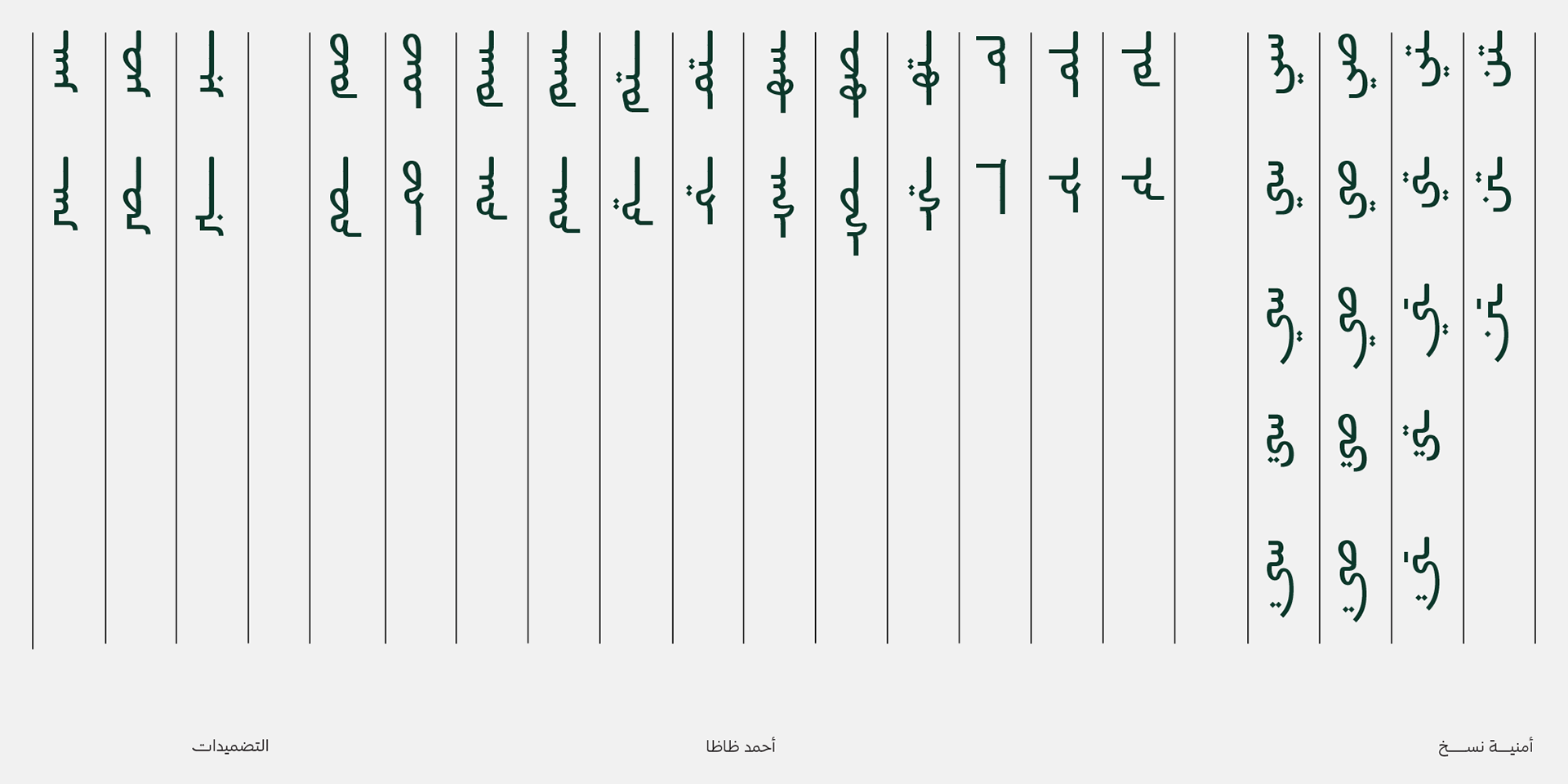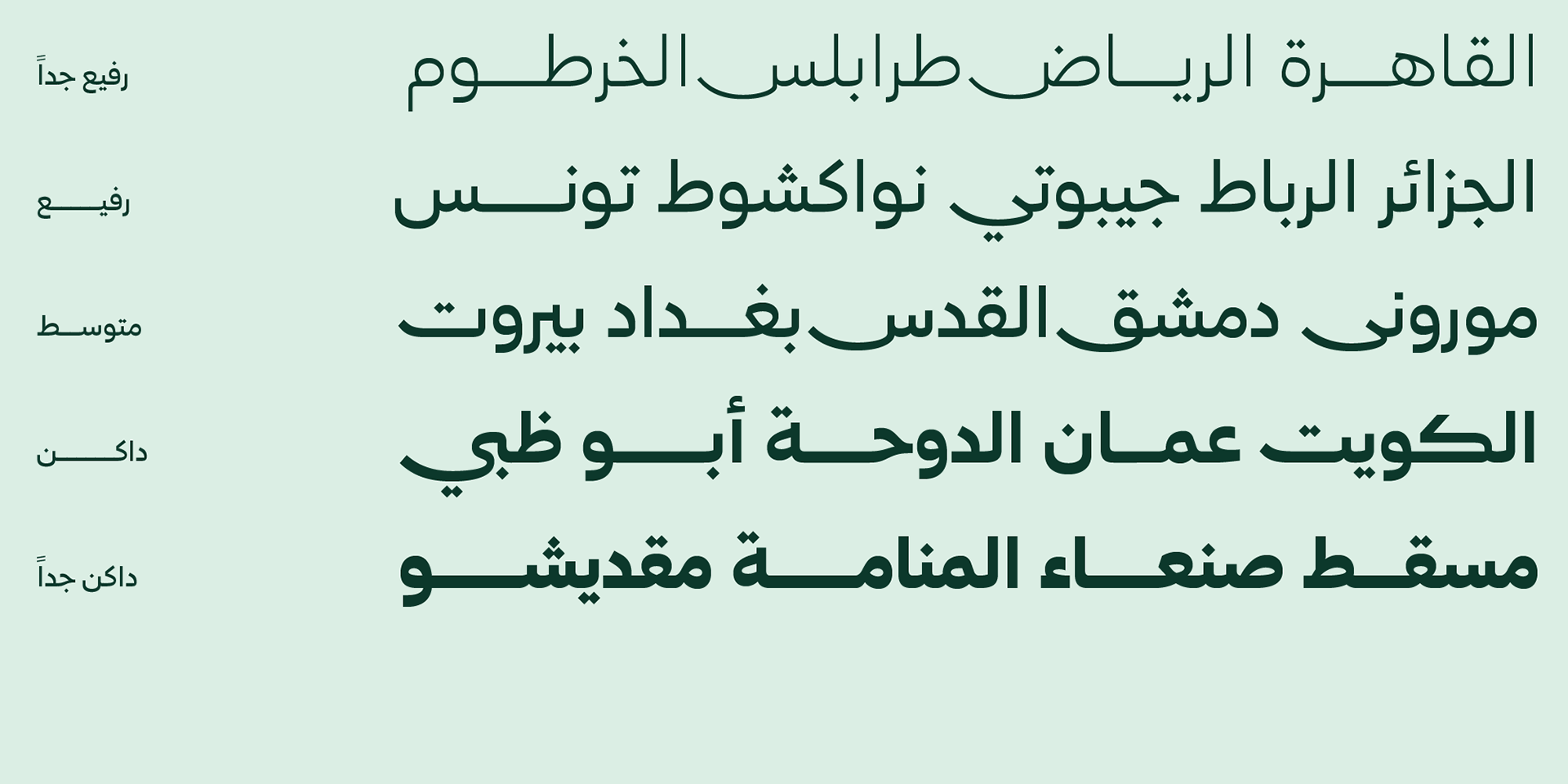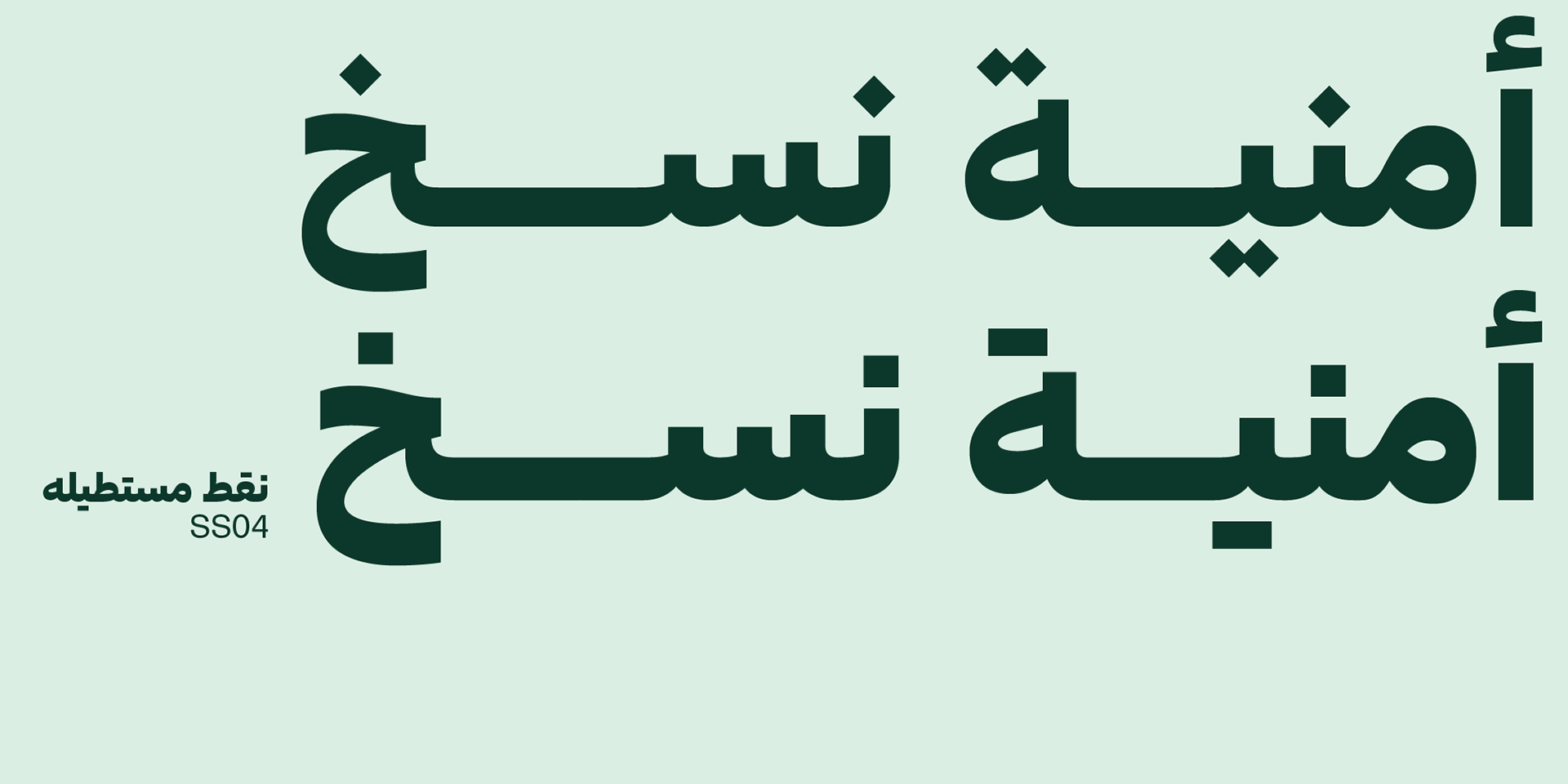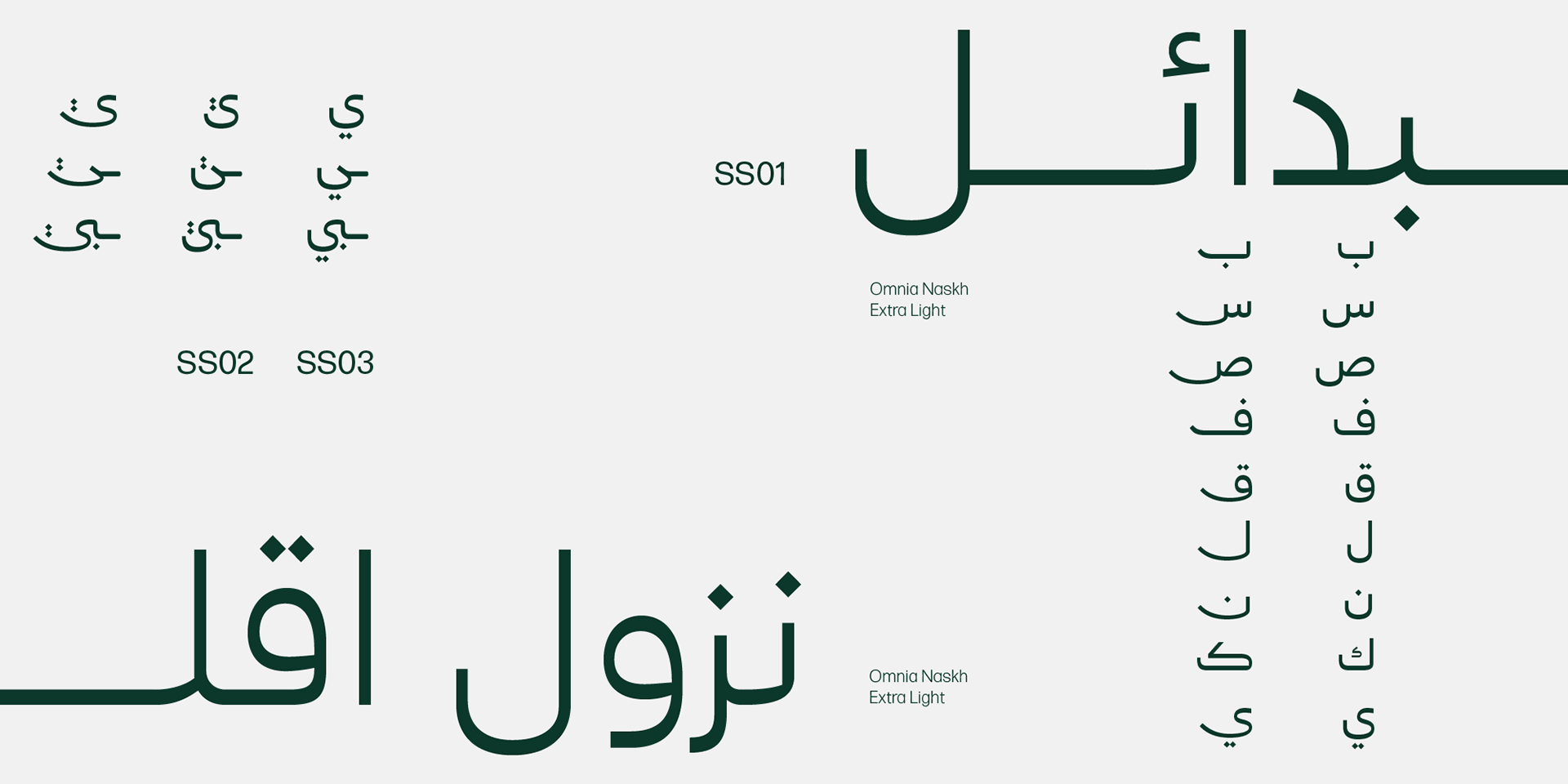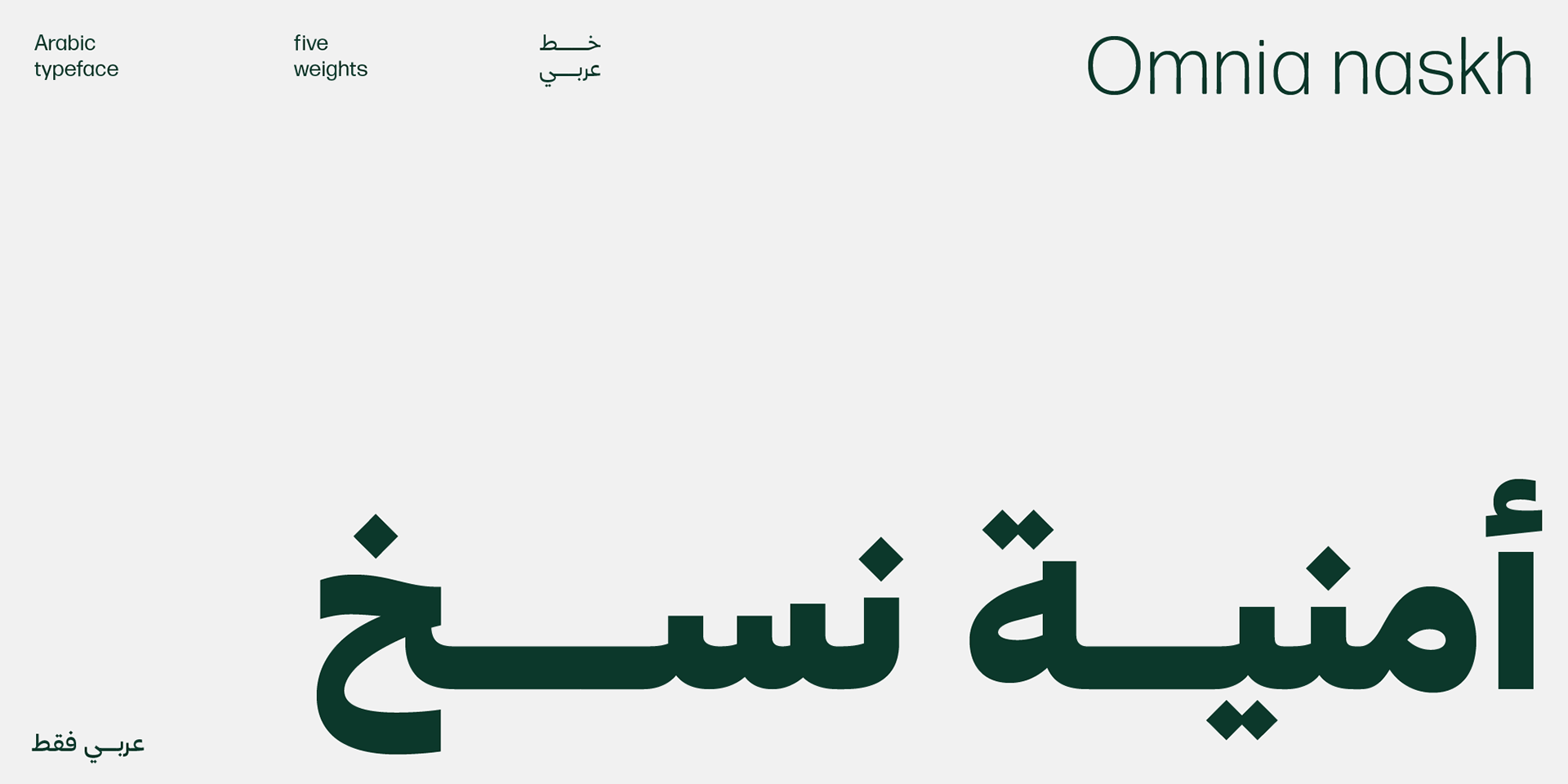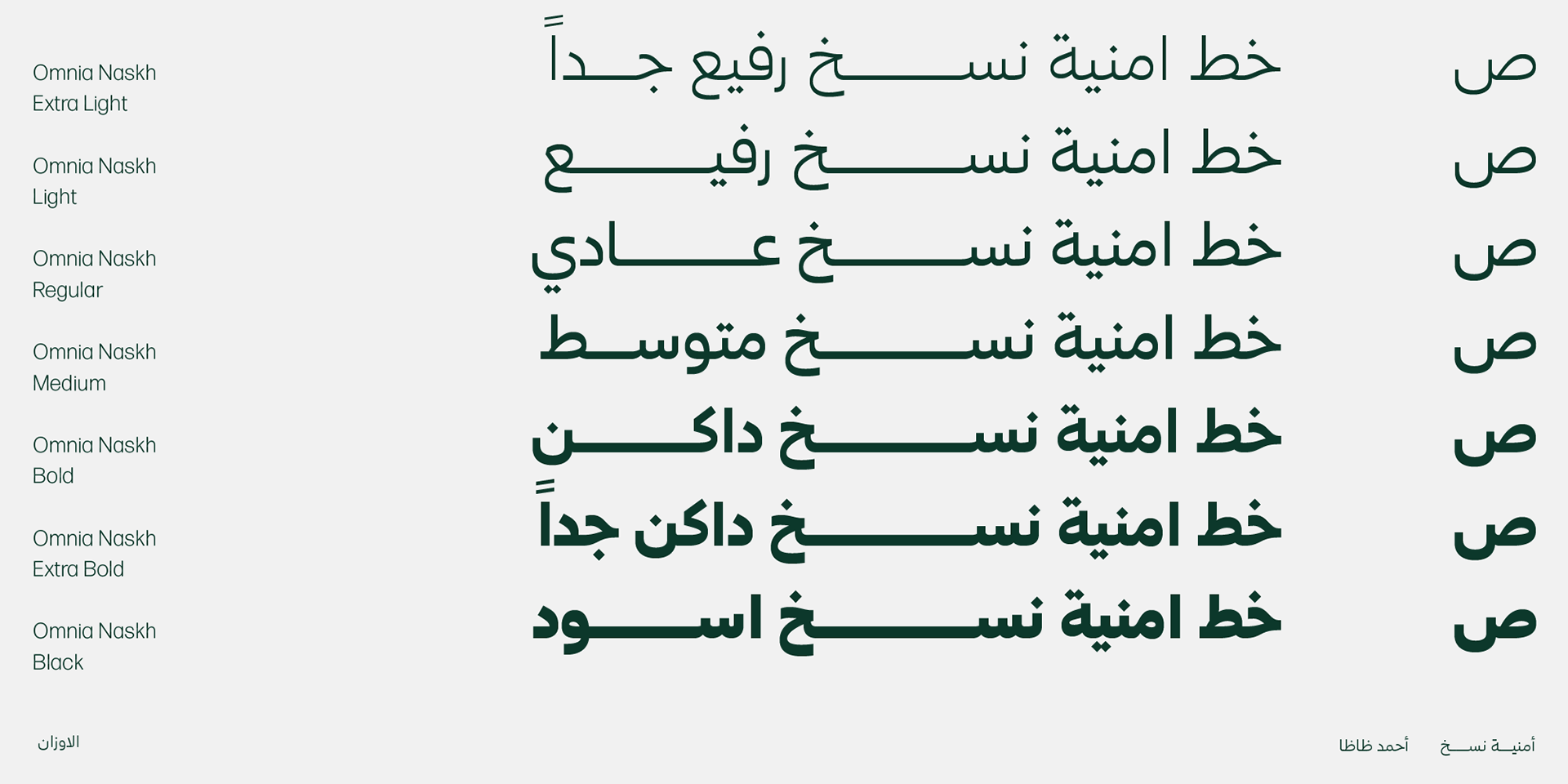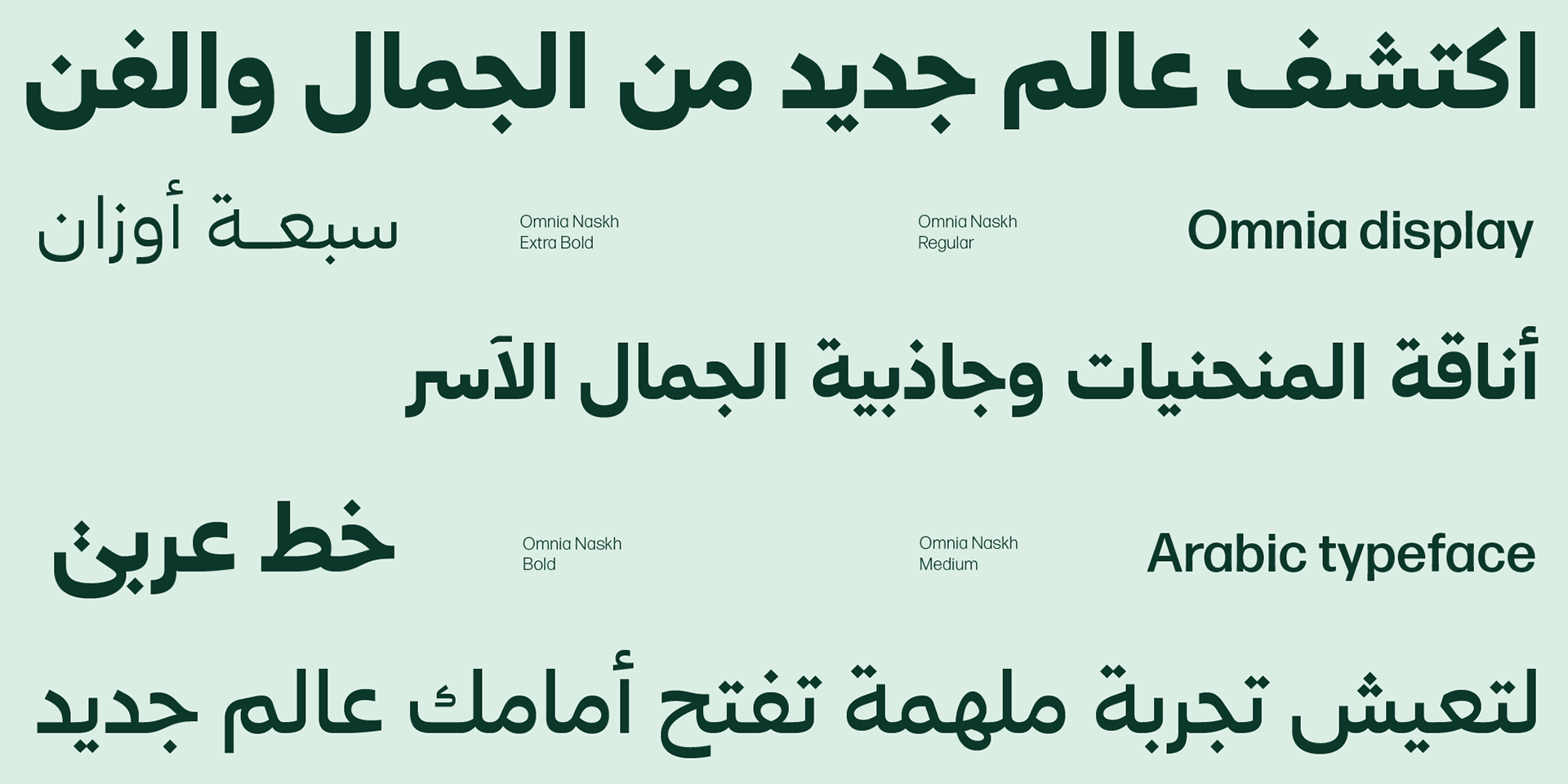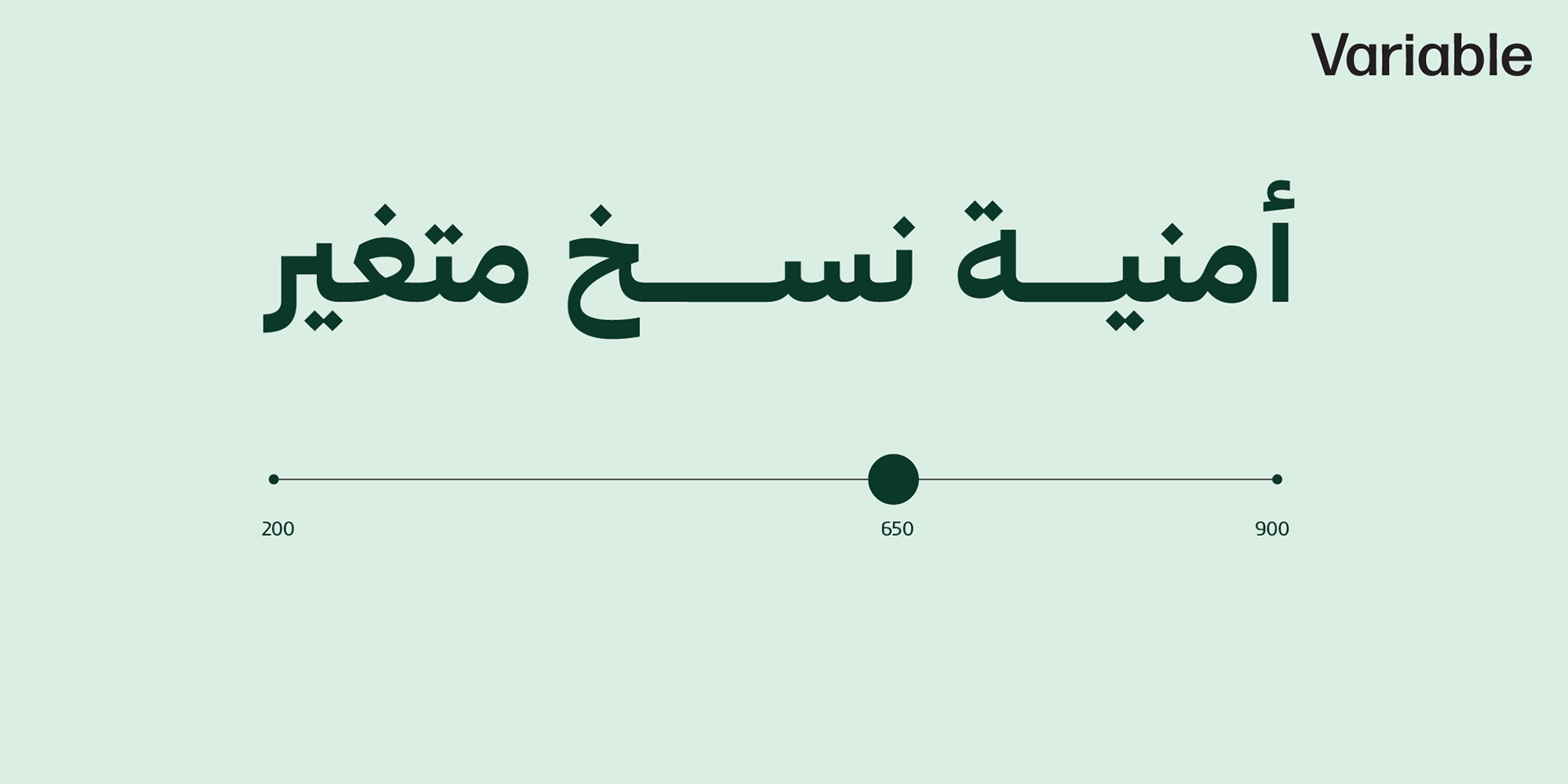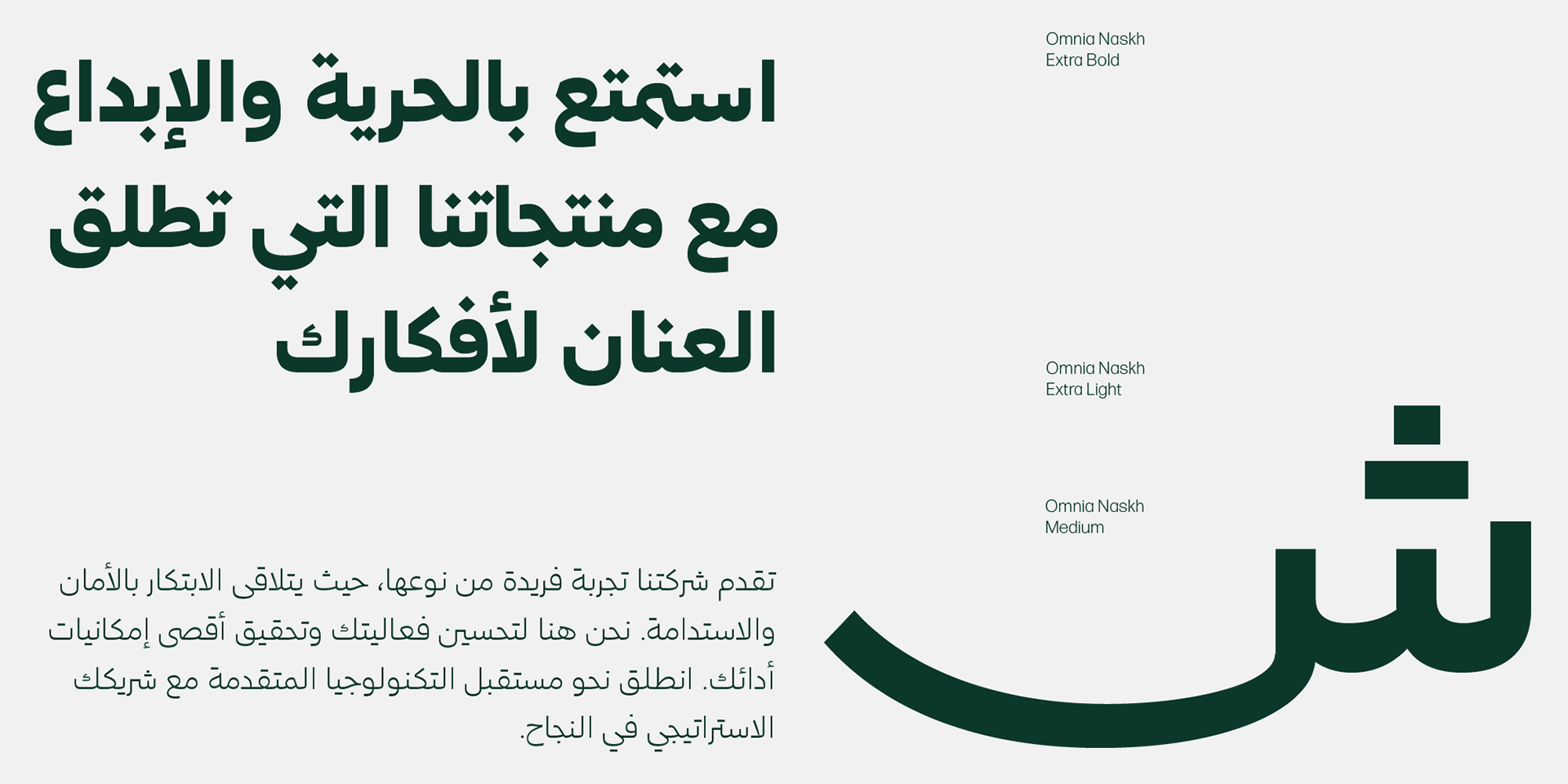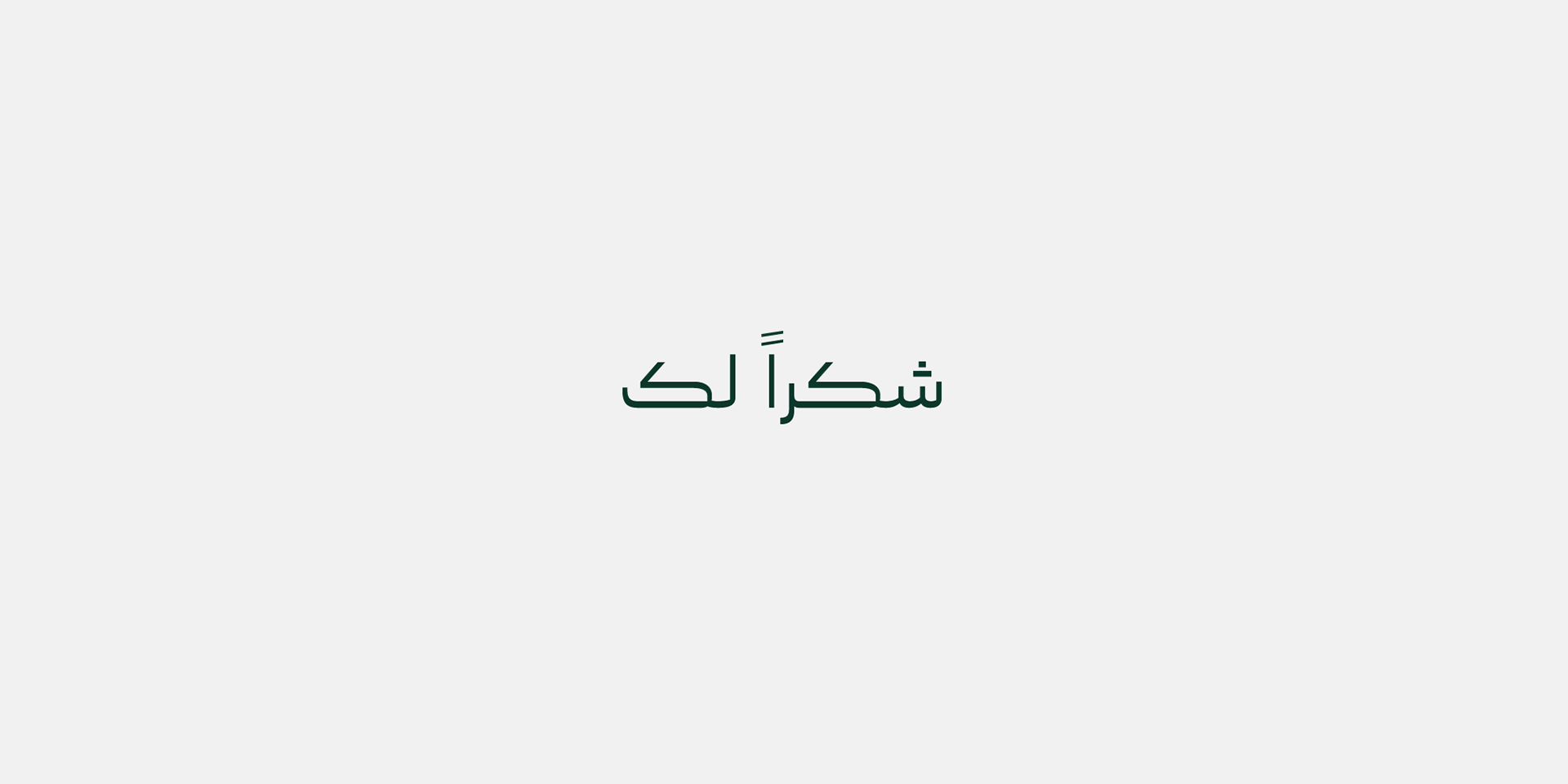
Omnia Naskh typeface - خط أمنية نسخ
أمنية نسخ هو خط عربي نسخ حديث يتميز بالأنحناءات الجمالية التي تعكس دقة التفاصيل. يجمع الخط بين الجمال والدقة في تجربة كتابية فريدة وغنية بالتفاصيل. تبرز مزايا أمنية نسخ بفضل وجود الحروف المركبة والحروف البديلة والحروف المرسلة. تسمح هذه الميزات للمصممين والكتاب بإنشاء نصوص أكثر تنوعًا وجمالًا وتعبيرًا. يتميز أمنية نسخ بوضوح في التصاميم الاحترافية، مما يضمن قراءة سهلة وفهمًا واضحًا. أمنية نسخ هو خيار احترافي يناسب مجموعة واسعة من الاستخدامات، بما في ذلك الطباعة والتصميم الجرافيكي والويب.